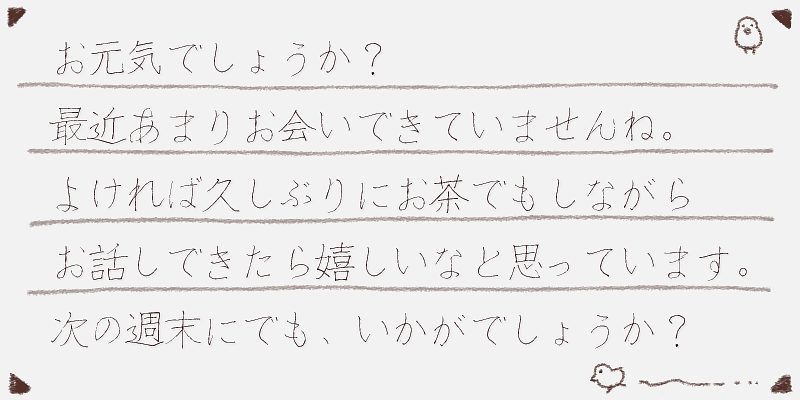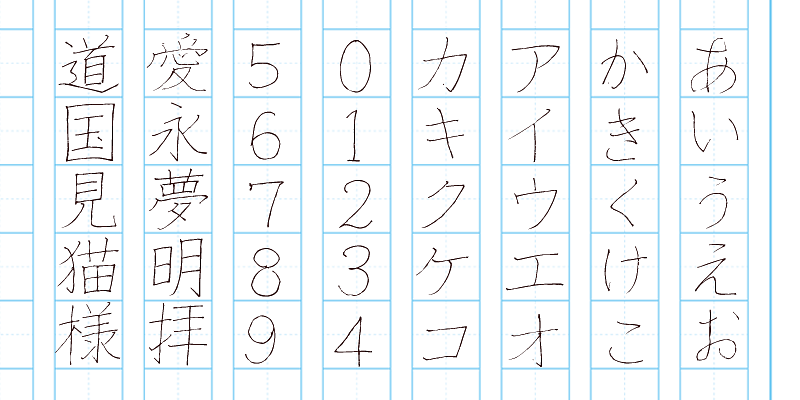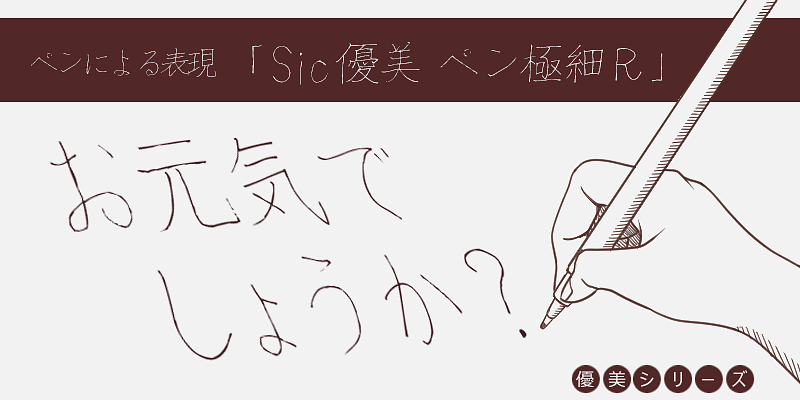
Fin da giovane, Eiichi Kawazoe ha studiato calligrafia sotto la guida del padre. Nel dipartimento speciale di calligrafia dell’università ha imparato i kanji da Kiseki Kosaka e Toson Amaishi e i kana da Kitsunan Tanibe e Kayu Hirata. Per proseguire la calligrafia giapponese fluente di kanji e kana iniziata con Yukinari, ha raccolto molti documenti antichi. Continua a perfezionare le sue abilità per preservare i caratteri tradizionali giapponesi che si sono sviluppati insieme all’ukiyo-e. Scrive anche i sigilli dei santuari e i cartellini dei rakugo e si cimenta con i caratteri usati nel sumo e nel kabuki.
Nota per la sua attenzione allo sviluppo di software, in particolare per l’industria dei servizi sanitari, nel 2007 Skill Information “S” si è trovata nel settore dei font grazie alla collaborazione con Techno Advance Co, Ltd.